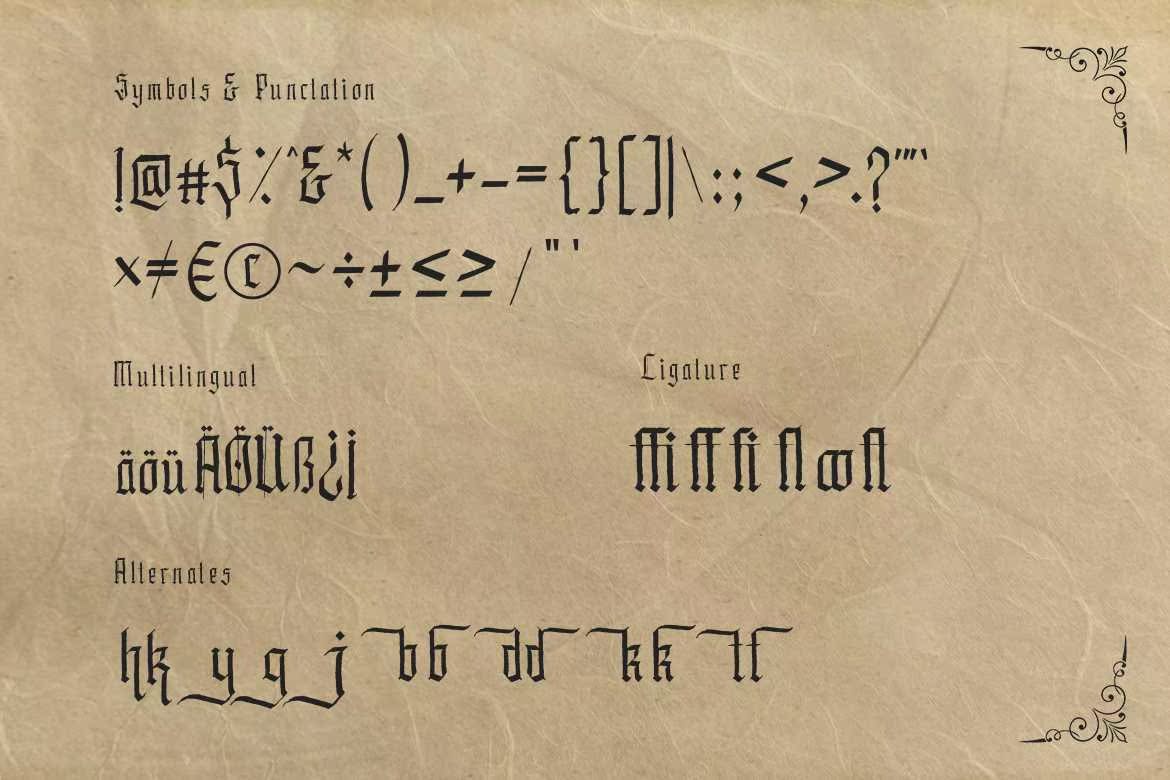
Harding Eis Bornf Romanorigin and Blackletter StyleFont。它是一种经典的年份风格,适用于徽标、品牌材料、t恤、印刷品、名片以及其他需要独特醒目字体的设计。完整版本下载:Harding Eis Bornf Romanorigin and Blackletter StyleFont。它是一种经典的年份风格,适用于徽标、品牌材料、,t恤、印花、名片以及其他任何需要独特醒目字体的设计。完整版本下载此处: